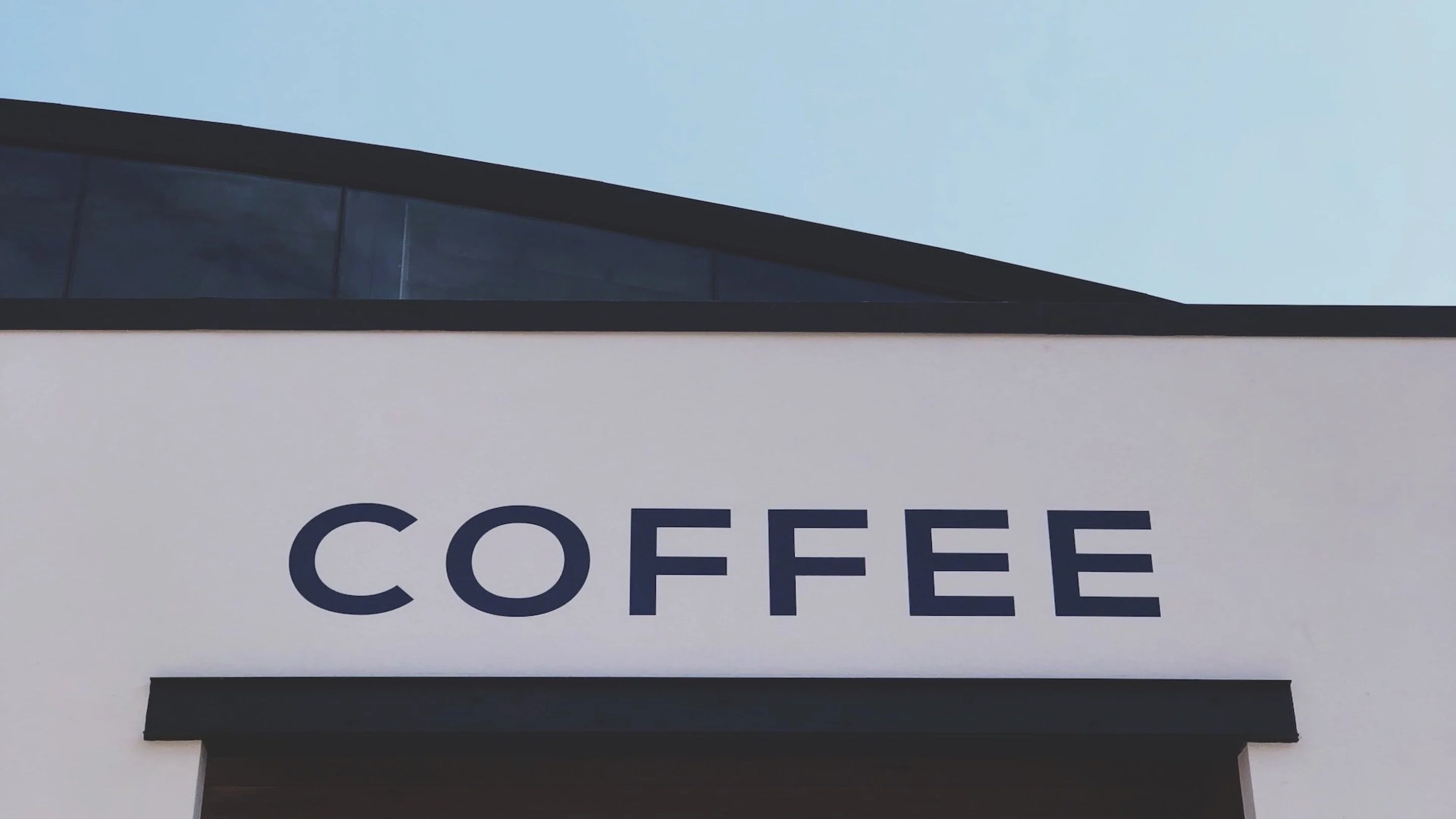
Muito mais do que apenas escolher uma fonte e um tamanho de ponto em alguns menus suspensos em seu computador, a tipografia é uma arte e uma habilidade com uma história rica que remonta a centenas de anos, quando as letras de madeira e metal foram usadas nas imprensas no século XX.
No entanto, encontramos a tipografia com muito mais facilidade do que nossos ancestrais; em qualquer dia, observamos uma variedade impressionante de fontes tipográficas antes de sair da cama, desde a leitura de e-mails, artigos de notícias cuidadosamente elaborados ou plataformas de redes sociais. O consumo de tipografia moderna geralmente é pouco mais do que uma ideia posterior para muitos de nós, mas é exatamente isso que torna a escolha tão crucial.
Sendo assim, os erros tipográficos tendem a fazer uma declaração maior do que uma boa tipografia. Os erros se destacam como um polegar dolorado, enquanto escolhas tipográficas cuidadosas se combinam de forma tão perfeita e imperdível com o design geral que você pode ignorá-las por completo. Dominar essa forma de arte é tanto evitar erros comuns e entender o equilíbrio quanto fazer declarações artísticas ousadas.
Em qualquer um dos casos, no entanto, você precisará estar ciente da terminologia tipografia, das principais técnicas e dos erros fundamentais para criar algo coeso. Reunimos alguns dos temas mais importantes a seguir em nosso guia completo para entender o que é a tipografia.
Em sua definição mais básica, tipografia é "o design ou a seleção de formas de letra a serem organizadas em palavras e frases a serem organizadas em blocos de texto que aparecem na impressão(abre em uma nova aba ou janela) em uma página" ou, em muitos casos, o que aparece na tela. , explica a Enciclopédia Britânica.
O objetivo fundamental da tipografia é apresentar o texto de uma forma que melhore (ou diminua, conforme o caso) a experiência de leitura do texto. A tipografia tem a capacidade de alterar a sua experiência de leitura, o que é absolutamente crucial para o consumo de tudo o que a inclui, desde artigos de papel e currículos até o design de embalagens.
Considere a sensação de ler um texto muito pequeno ou que tem um espaço mínimo entre as letras, em vez de um texto que é elaborado da maneira que você espera: fonte e tamanho uniformemente espaçados. Ou considere como a tipografia em um pôster em cores loucas e organizada de forma inteligente pode desafiar sua percepção de um produto ou marca. O verdadeiro poder da tipografia está em sua capacidade de alterar a forma como você se sente em relação a uma mensagem que está sendo transmitida.
Uma fonte é um conjunto de caracteres de texto imprimíveis ou exibidos em um estilo específico, conhecido como família de fontes. Hoje, os termos "fonte" e "tipo de letra" são usados de forma intercambiável, mas com diferenças(abre em uma nova aba ou janela) antigas. Em termos simples, uma fonte é design: é o que você vê; uma fonte é como esse design é entregue: é o que você usa. Embora essa distinção tenha se tornando menos importante com o surgimento da editoração eletrônica, é importante entender a diferença histórico.
Uma fonte pode ser aplicada em todos os tamanhos diferentes e ser usada para criar uma hierarquia visual(abre em uma nova aba ou janela). A hierarquia visual é uma função importante da legibilidade do texto. Considere um diário e seu layout da manchete para ampliar uma mensagem focal, o subtítulo para resumir(abre em uma nova aba ou janela) a peça e o texto do parágrafo para transmitir a mensagem por completo. O princípio da proporção dourada(abre em uma nova aba ou janela) é aquele que você pode aplicar para obter esse equilíbrio.
O peso de uma fonte determina a espessura ou a finura dos caracteres exibidos. As fontes estreitas e finas podem criar um bom contraste entre um título mais grosso e mais ousado e o corpo do texto, mas elas têm suas próprias desvantagens, pois podem ser difíceis de ler em um corpo de texto pequeno devido à aparência fraca.
A ascensão é a raiz vertical que se estende acima da linha média de uma fonte. Em outras palavras, a parte mais alta de uma letra minúscula ou a parte superior de uma letra maiúscula. Textos menores, de introdução ou de apoio geralmente são melhores nesse espaço de destino.
O descendente é a parte da letra que se estende abaixo da linha de base de uma fonte. Subtítulos ou textos menos importantes se encaixam bem nesse espaço, um simples slogan ou embelezamento.
A serifa é uma fonte com pequenas bordas decorativas no final das letras. Elas têm um visual mais tradicional e sofisticado. As fontes com serifa são adequadas para textos longos, pois são fáceis de ler.
Uma fonte sem serifa é uma fonte geométrica sem detalhes decorativos, traços adicionais ou esporão no final das letras. Eles têm um visual mais moderno e minimalista e são ótimos para títulos.
Uma fonte cursiva reproduz o curso de um pincel, geralmente vinculando letras. A aplicação de um roteiro pode dar um toque especial ao seu design. As fontes cursivas criam uma combinação dinâmica e interessante quando combinados com fontes sem serifa.
Pode ser fácil usar em excesso esses pesos e estilos (como negrito, itálico ou letras maiúsculas). Esses estilos podem ser ótimos para dar ênfase ao texto, talvez para fazer com que ele se destaque visualmente, mostrar sua importância ou reproduzir padrões de fala. Só não use todos eles em uma passagem de texto; Parece que você está se esforçando demais para transmitir a sua mensagem e pode parecer falta de educação para os leitores. A ocasião deve ser rara em que você precise de mais de um tipo.